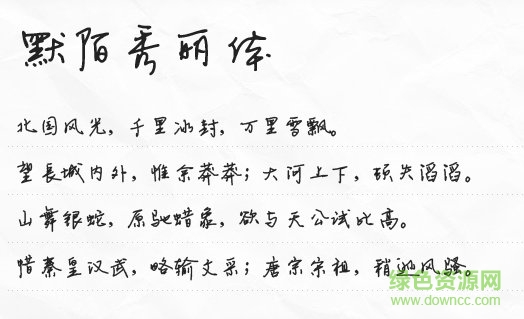
默陌秀麗筆體是一款字跡飄逸但不潦草、娟秀而不失大氣的鋼筆書法字體,給人堅韌而細膩的視覺呈現(xiàn),是一款讓你眼前一亮的手寫字體,快來綠色資源網(wǎng)下載收藏吧!
默陌秀麗字體,字跡濃重二兼具清麗之美,連貫灑脫卻不失飄逸之風(fēng),可以廣泛運用于排版印刷、文字設(shè)計等領(lǐng)域,讓你的圖文內(nèi)容增添一絲古聲古色之美!